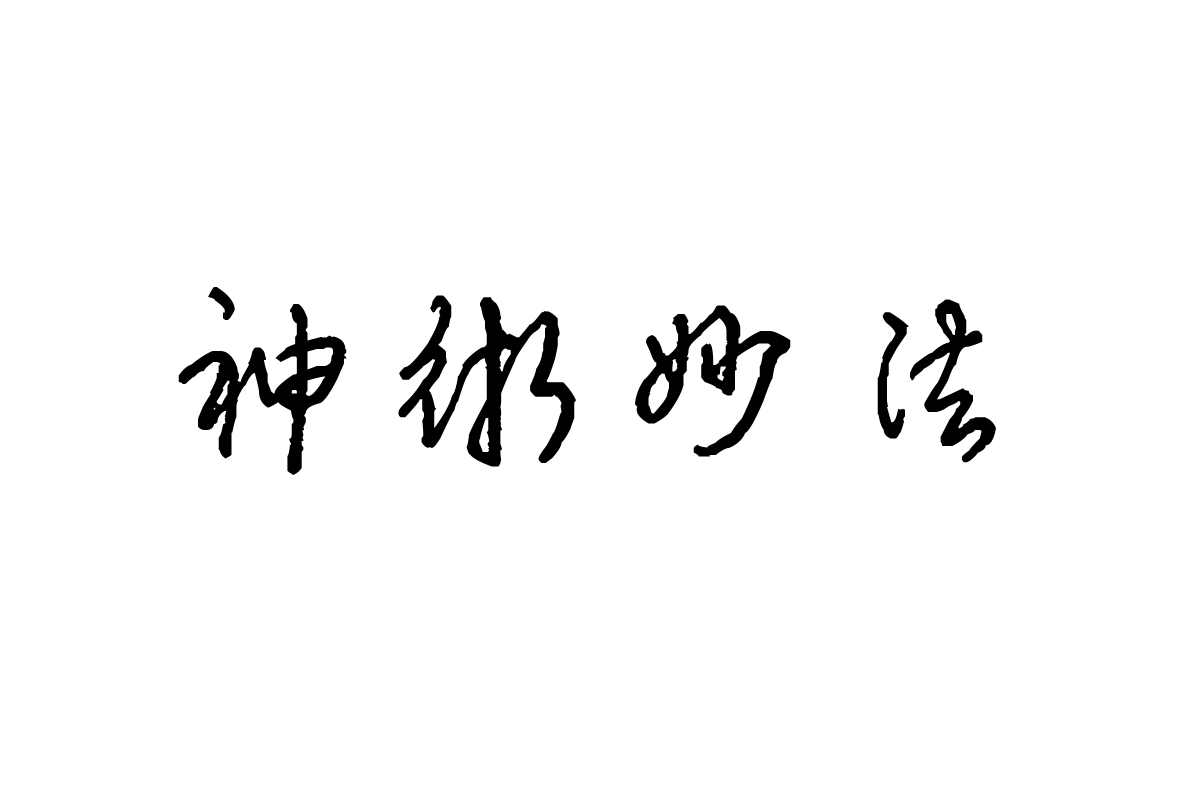
汉呈波波硬草字体是一款具有现代感的中文字体,其特点是字形结构紧凑、笔画清晰。这种字体适合用于需要强调文字的场合,如标题、广告等。
汉呈波波硬草字体的特点如下:
1. 字形结构紧凑:汉呈波波硬草字体的字形结构紧凑,笔画之间没有多余的空间,使得文字看起来更加简洁明了。
2. 笔画清晰:汉呈波波硬草字体的笔画清晰,每个笔画都有明显的起笔、转折和收笔,使得文字阅读起来更加流畅。
3. 适用于多种场合:汉呈波波硬草字体适用于各种场合,如标题、广告、新闻等。它的现代感特点使其在商业和时尚领域尤为受欢迎。
4. 易于识别:汉呈波波硬草字体的字形设计独特,易于识别,使得读者能够迅速抓住文字的重点。
总之,汉呈波波硬草字体以其独特的字形结构和现代感特点,成为了一种受欢迎的中文字体。